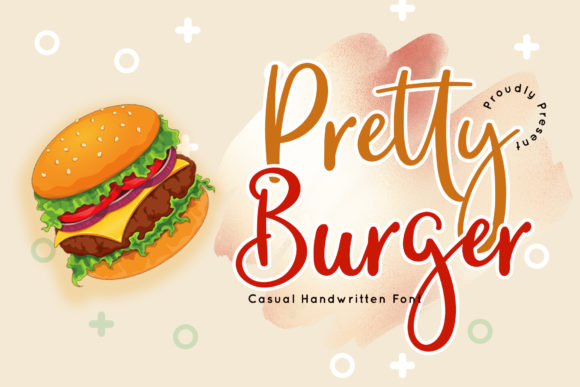
Creativefabrica Pretty Burger Font
[Creativefabrica] Pretty Burger Font
Симпатичный бургер - это простой, случайный рукописный шрифт.
Он выглядит потрясающе на благодарственных открытках, цитатах, поздравительных открытках, логотипах, визитках и любом другом дизайне, который нуждается в рукописном прикосновении.